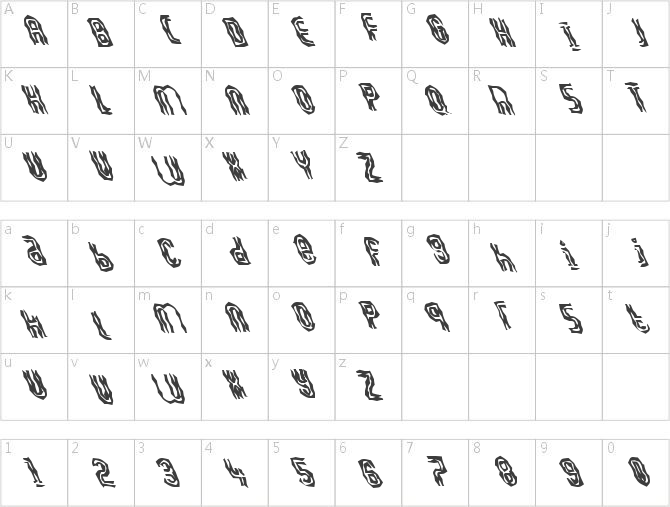
FZ WACKY 41 LEFTY 詳情頁(yè)
FZ WACKY 41 LEFTY字體字庫(kù)是一款讓人賞心悅目、百看不厭的英文字體,適合各類(lèi)廣告和產(chǎn)品包裝設(shè)計(jì)應(yīng)用,字體大小0.08MB,格式為ttf字體,上傳用戶(hù)是小籃子,作者/版權(quán)方為未知